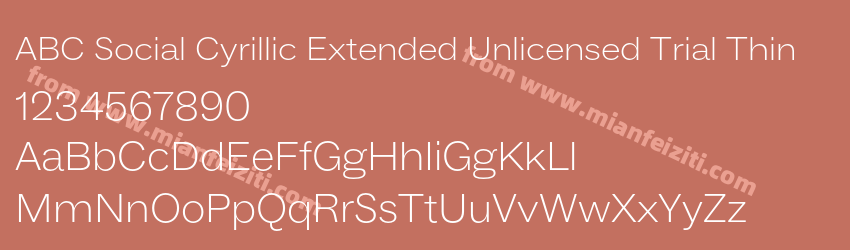
ABC Social Cyrillic Extended Unlicensed Trial Thin
字体名称: ABC Social Cyrillic Extended Unlicensed Trial Thin
本款“ABC Social Cyrillic Extended Unlicensed Trial Thin”是一款书写很新颖的字体,字体大方,适合各种设计作品使用!欢迎下载!